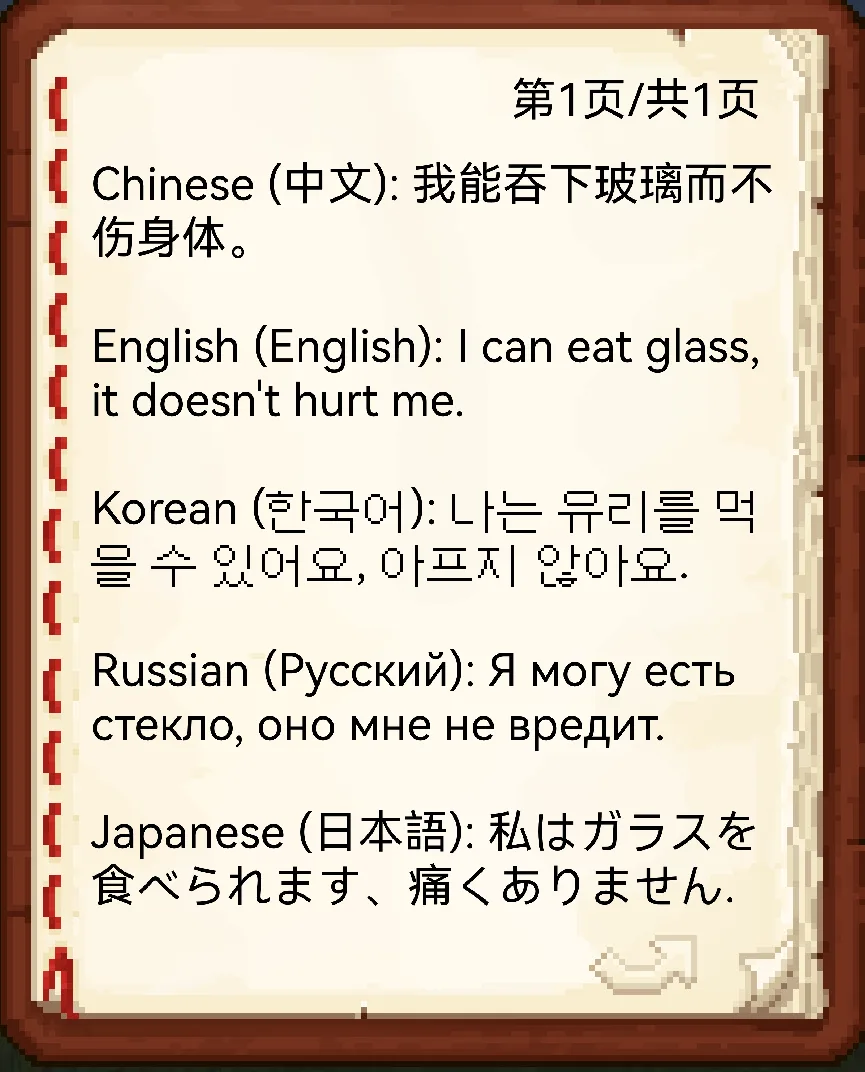
XPlus Font Pack
XPlus Font Pack заменяет стандартные шрифты Minecraft на плавный и элегантный Source Han Sans, улучшая читаемость и стиль в игре. Поддерживает множество языков, включая английский, корейский, русский и китайский.
Что дает этот resource pack
XPlus Font Pack — это пакет шрифтов для Minecraft, разработанный командой XPlus, который интегрирован в модпак XPlus Series. Он преобразует внутриигровые шрифты в гладкий и элегантный шрифт Source Han Sans, устраняя скучные стандартные варианты и создавая атмосферу чёткости и стиля.
С этим пакетом игроки могут наслаждаться плавным игровым процессом на нескольких языках, так как он поддерживает широкий диапазон языковых символов. Читаемость и согласованность текста обеспечиваются без необходимости загрузки дополнительных модов.